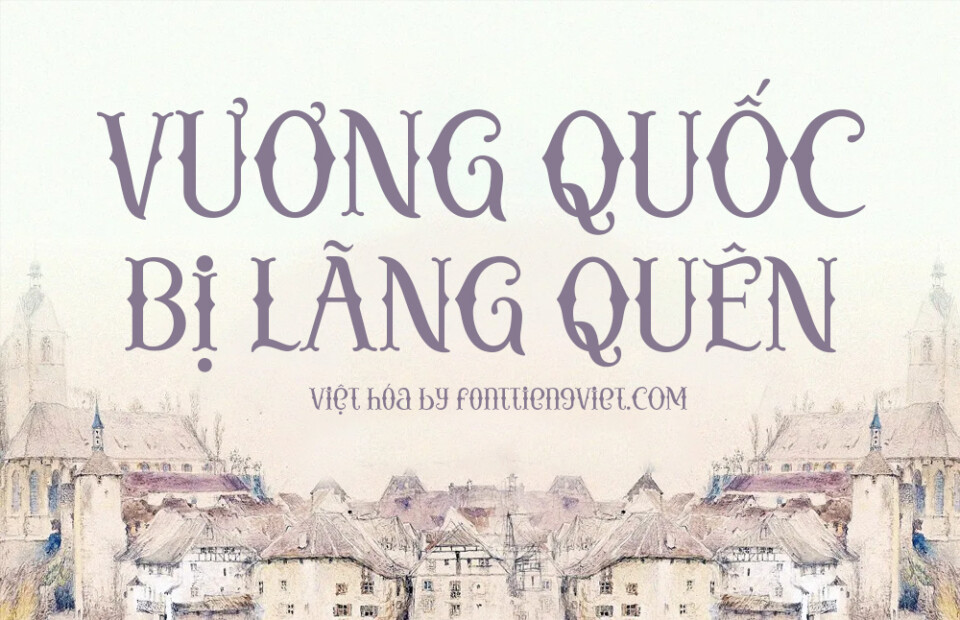
Font Việt hóa 1FTV VIP Little Witches – Font Việt hóa vintage
Font Việt hóa 1FTV VIP Little Witches – Font Việt hóa vintage: Nét đẹp cổ điển cho thiết kế học đường
Giới thiệu về Font Việt hóa 1FTV VIP Little Witches – Font Việt hóa vintage
Trong thế giới đồ họa hiện đại, việc tìm kiếm một Font Miễn Phí mang đậm chất nghệ thuật nhưng vẫn đảm bảo tính ứng dụng cao là điều không hề dễ dàng. Font Việt hóa 1FTV VIP Little Witches – Font Việt hóa vintage chính là câu trả lời hoàn hảo cho những ai đang theo đuổi phong cách thiết kế cổ điển pha chút huyền bí. Đây là bộ phông chữ được tinh chỉnh kỹ lưỡng, hỗ trợ đầy đủ bộ gõ tiếng Việt, giúp các bạn học sinh và giáo viên dễ dàng tạo ra những sản phẩm trình bày ấn tượng mà không lo lỗi font.
Đặc điểm nổi bật của bộ Font Việt hóa vintage này
Thiết kế thủ công tinh tế
Font Việt hóa 1FTV VIP Little Witches – Font Việt hóa vintage sở hữu các đường nét thanh mảnh nhưng không kém phần sắc sảo, gợi nhớ đến những trang sách cũ hay các tấm bảng thông báo tại trường học xưa. Sự kết hợp giữa yếu tố thủ công và công nghệ số tạo nên một diện mạo vừa thân thuộc vừa sang trọng.
Khả năng ứng dụng đa dạng trong giáo dục
Nhờ tính thẩm mỹ cao, bộ chữ này rất phù hợp để thiết kế bìa tiểu luận, làm thiệp chúc mừng thầy cô hoặc trang trí bảng tin lớp học. Kiểu dáng vintage giúp nội dung truyền tải trở nên có chiều sâu và thu hút người xem hơn ngay từ cái nhìn đầu tiên.
Lưu ý khi sử dụng Font Việt hóa 1FTV VIP Little Witches – Font Việt hóa vintage